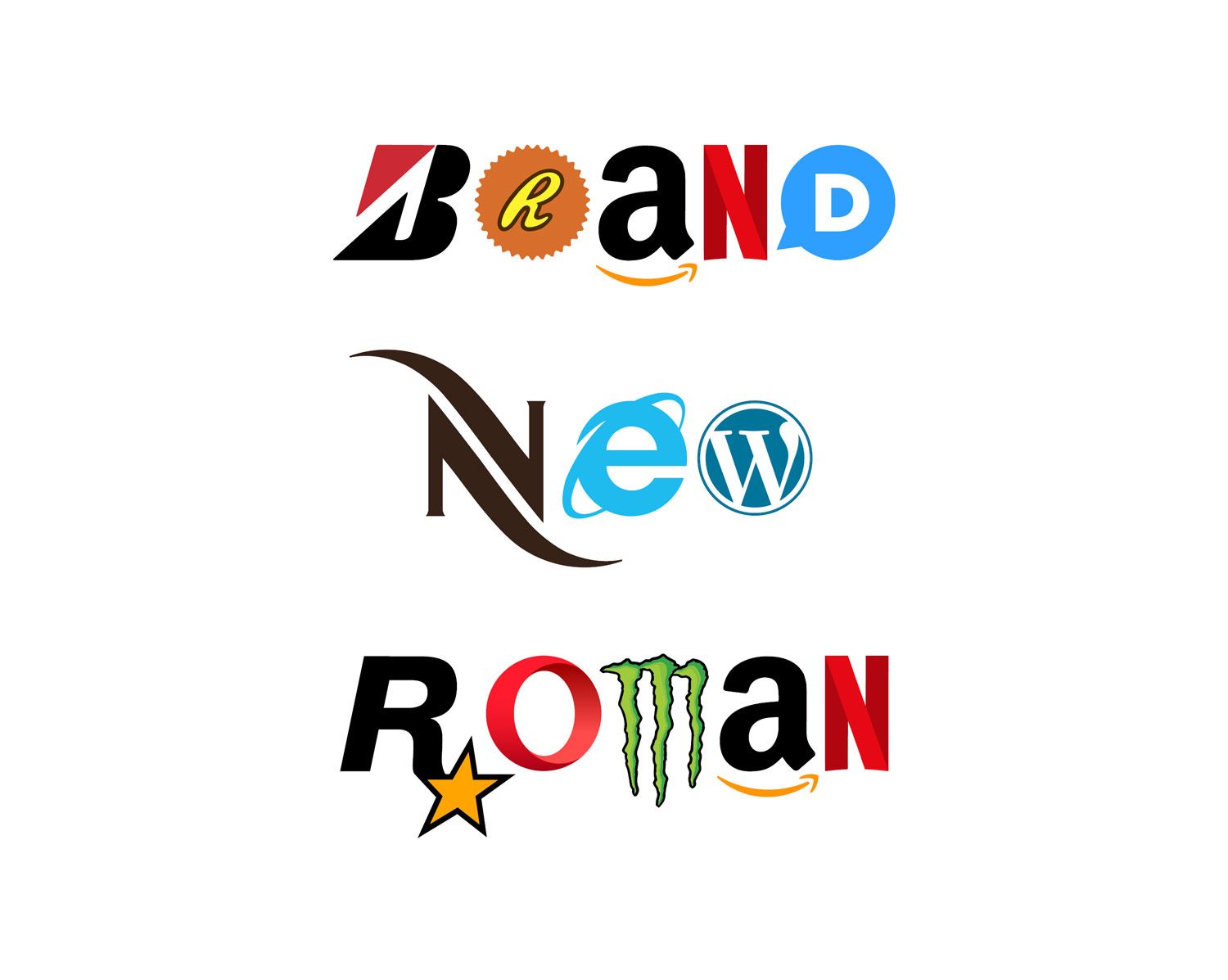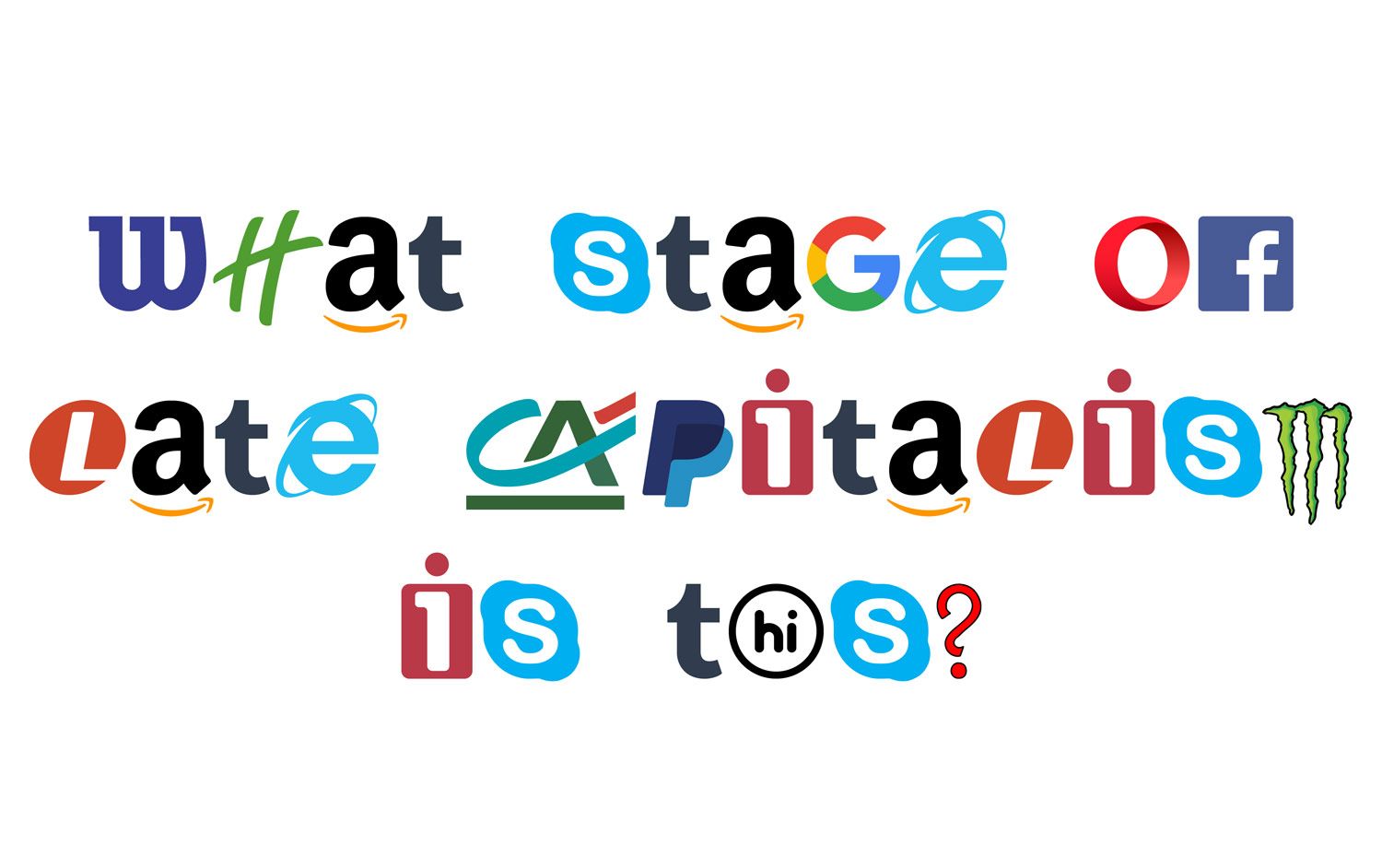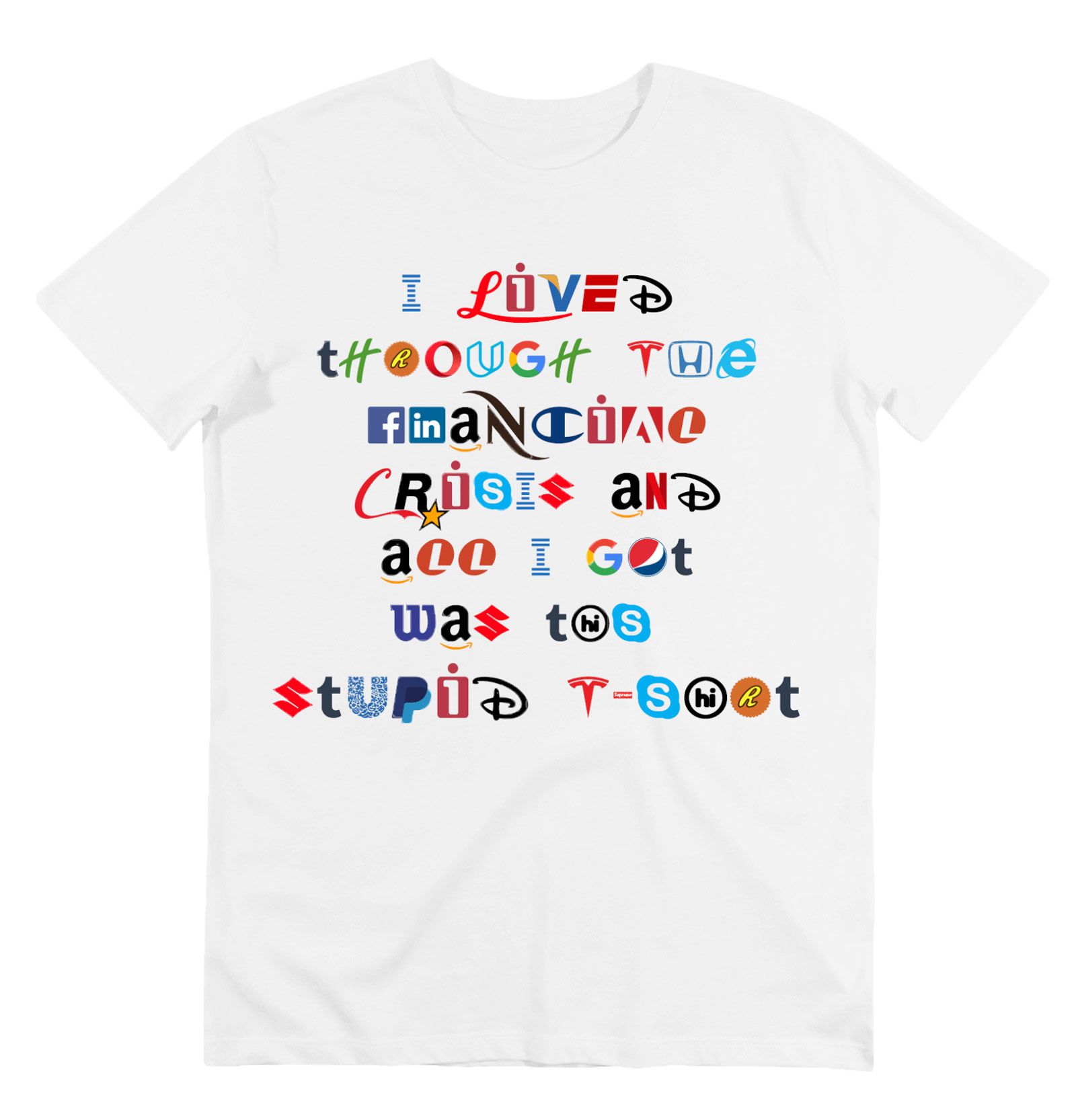
'Brand new roman', la tipografía más corporativa del mundo
La tipografía Brand New Roman, creada por Hello Velocity, se autoproclama como la fuente más corporativa del mundo.
En la era en la que resulta prácticamente imposible mirar a nuestro alrededor y no ver nuestro entorno plagado de logotipos y marcas, era solo cuestión de tiempo que alguien cayese en la cuenta de que podría crearse una tipografía uniendo las letras de los diferentes emblemas. Fue así como nació 'Brand new roman', una tipografía experimental creada a partir de logotipos de algunas de las marcas más globalmente reconocidas de la historia.
Coca-Cola, Facebook, Amazon, Pepsi, Google, Paypal, Disney... y así hasta completar los 76 glifos que componen esta tipografía. Cada letra ha sido tomada prestada del logotipo de una grande marca para formar un alfabeto que, según sus propios creadores, responde a una realidad en la que prácticamente todo está esponsorizado. Se trata de la creación de Hello Velocity, un estudio creativo neoyorquino especializado en campañas que se salen de lo corriente, como esta.
La tipografía Brand new roman está disponible en dos versiones, una en blanco y negro y otra en color, que solo está soportada, esta última, por algunas versiones de los programas de edición más habituales y solo en algunos navegadores web.